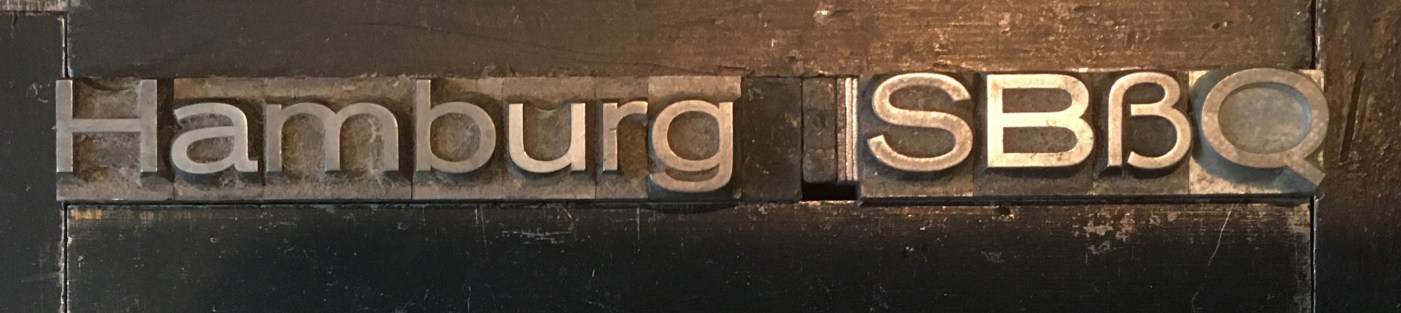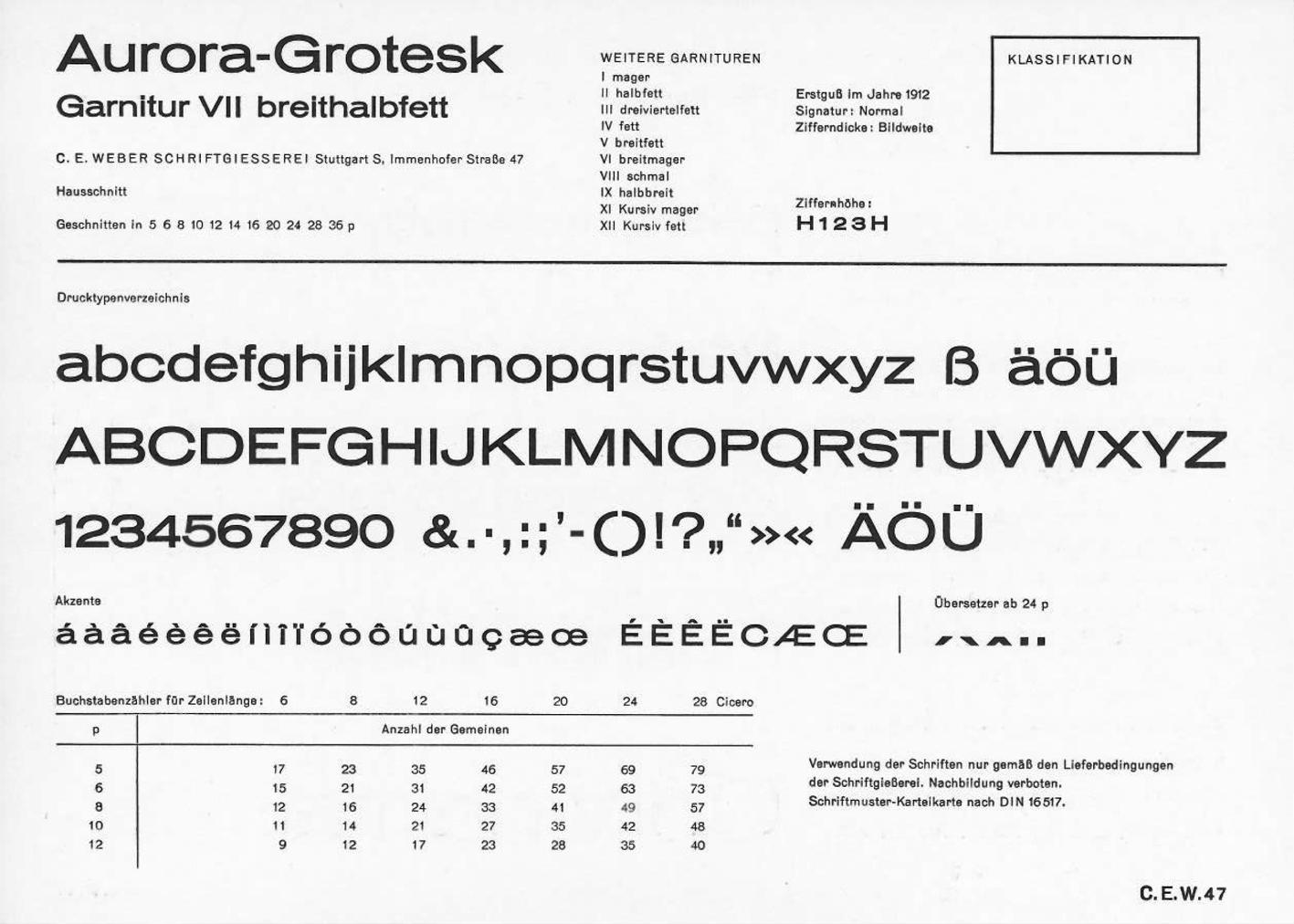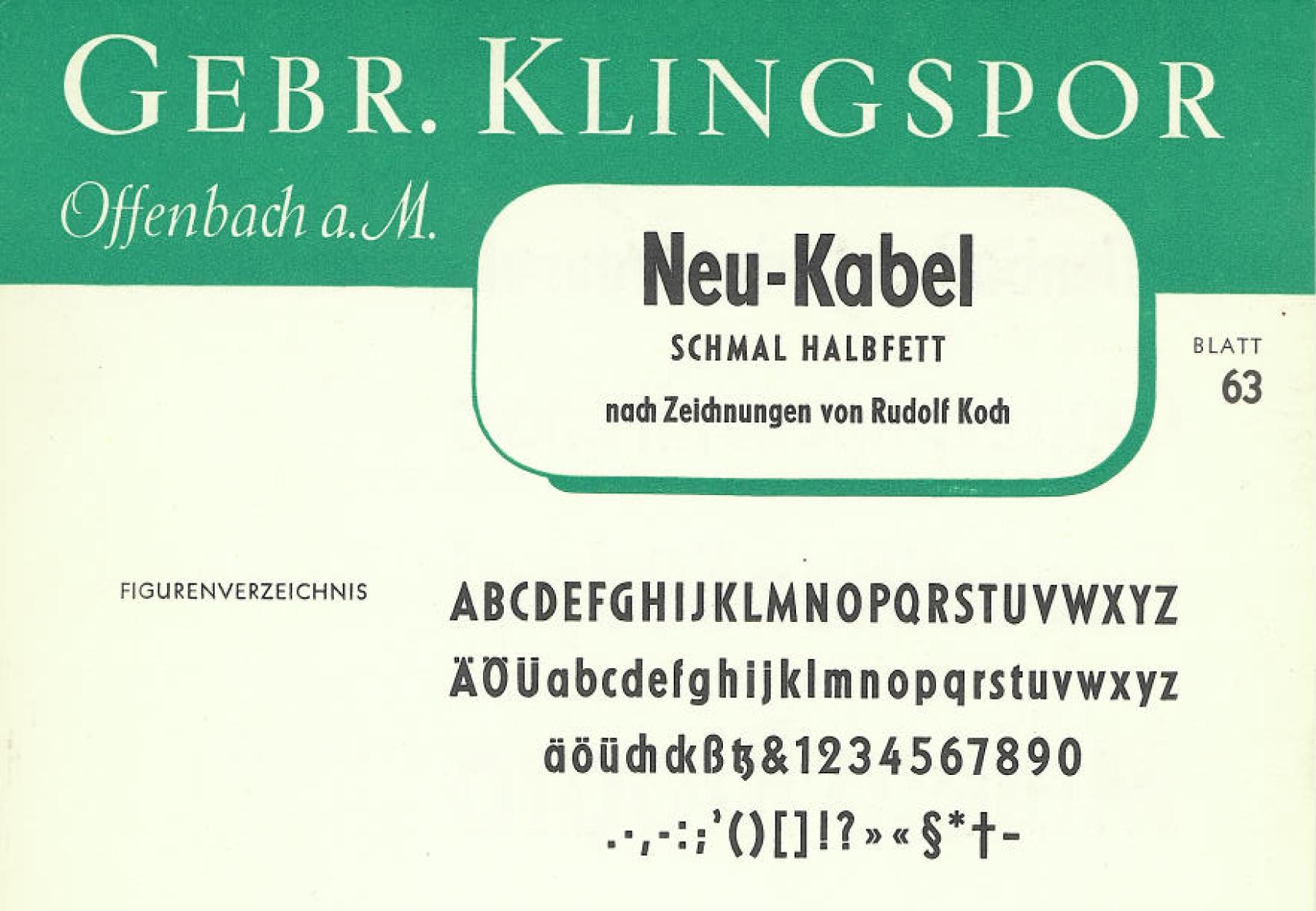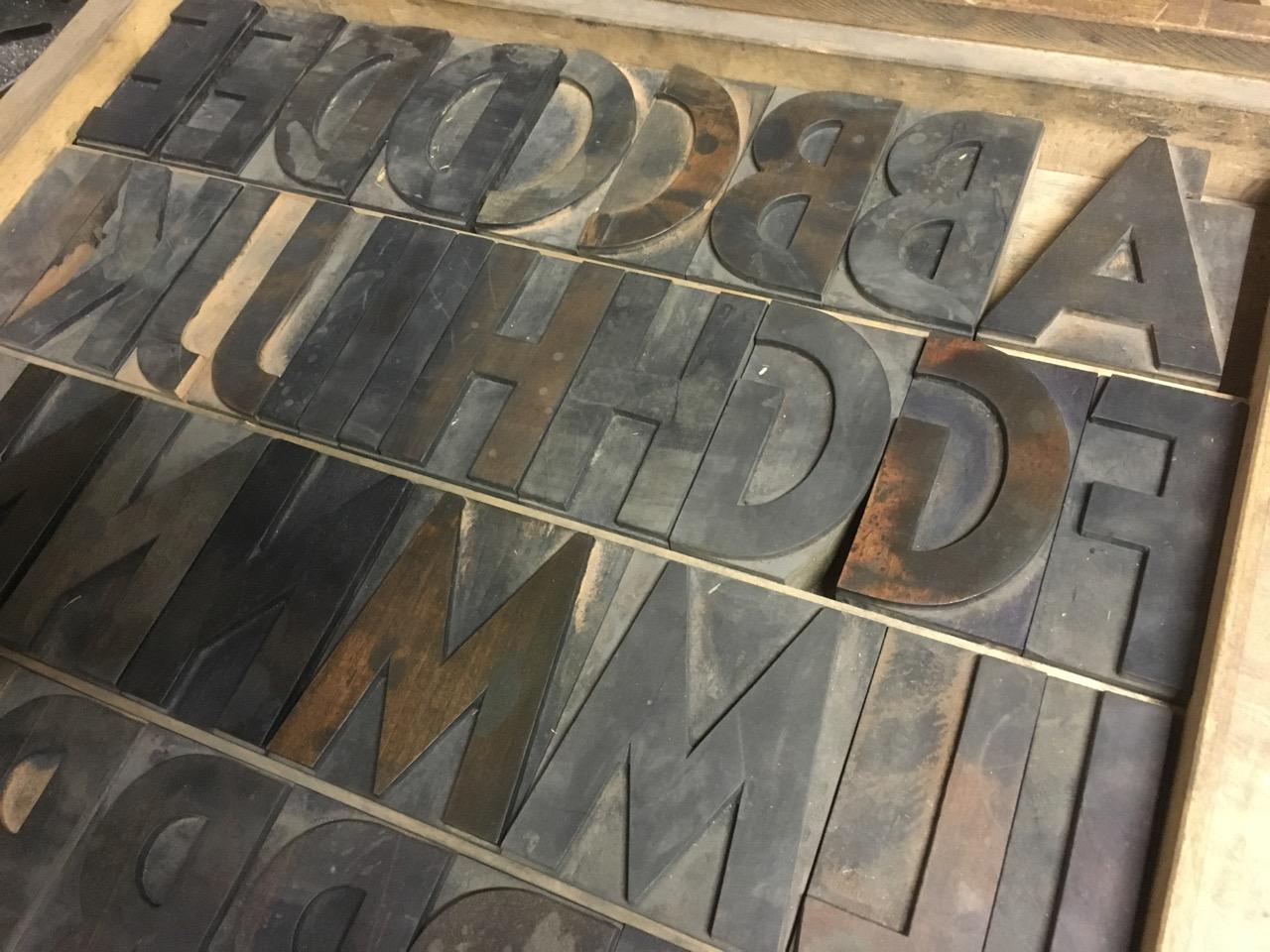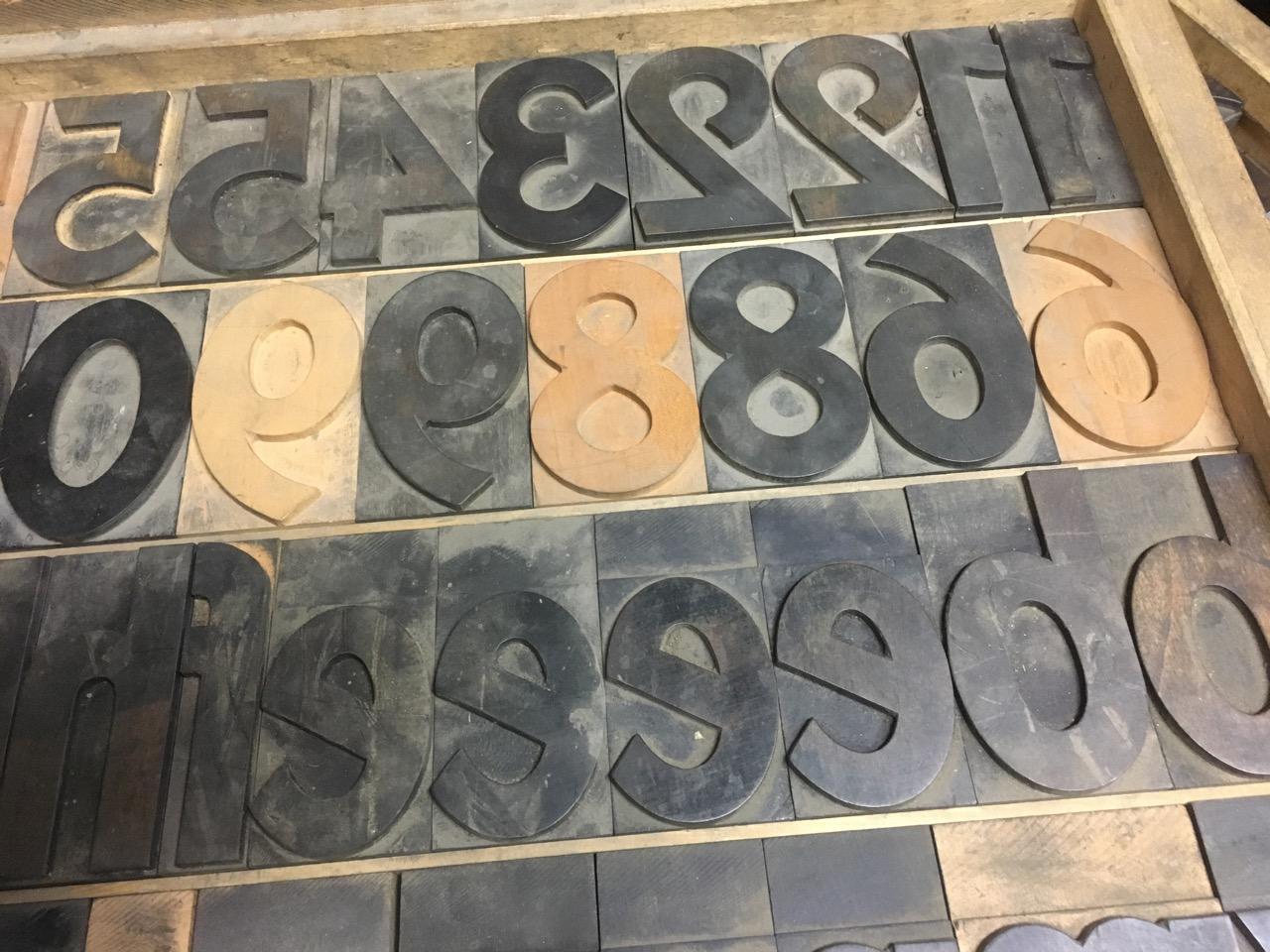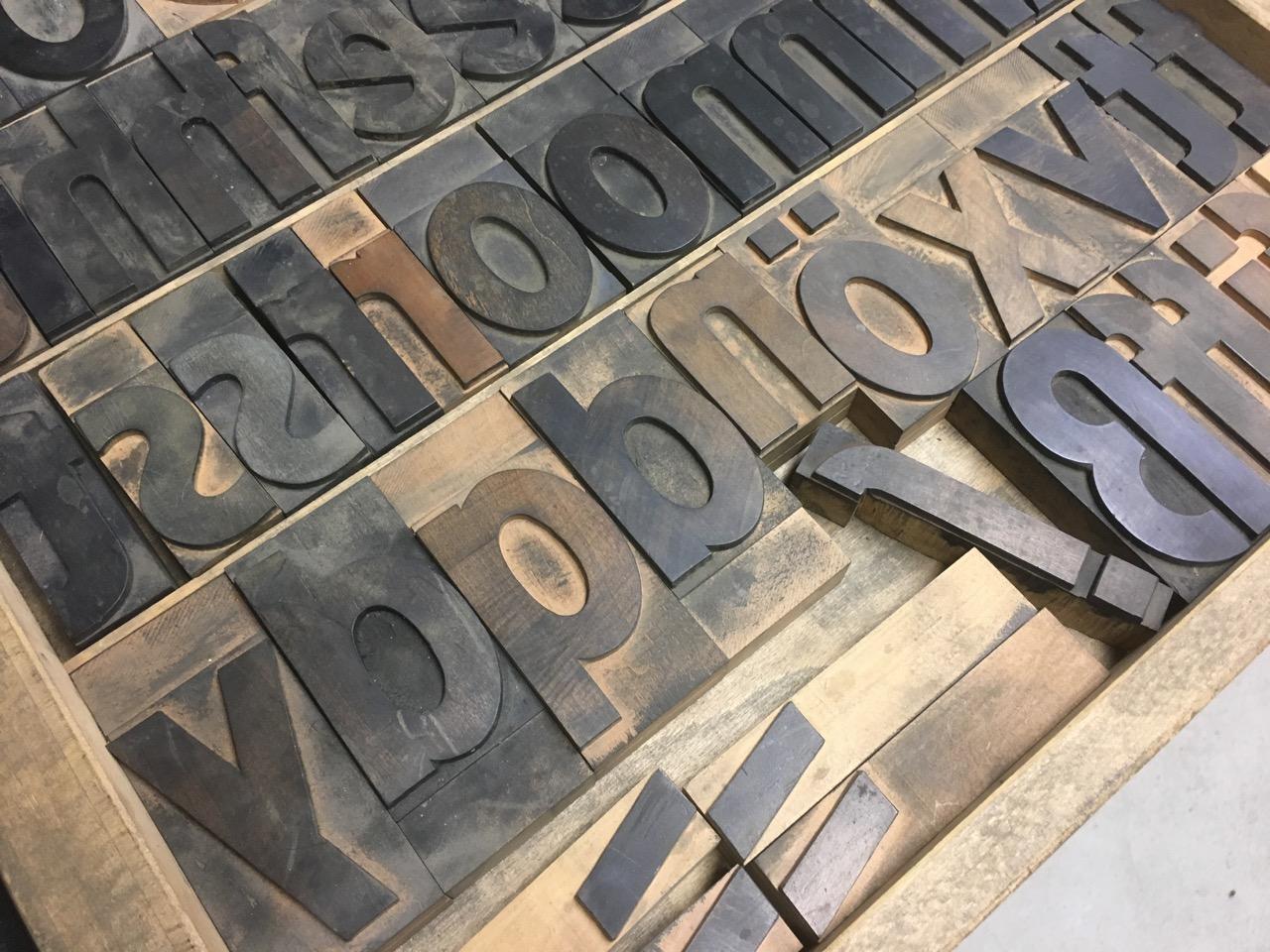
Identifikation Holzschriften
Unten ev. Akzidenz Skelett.
Korrigiere mich: es dürfte die hf.? breite Aurora Grotesk sein.
Tja, schwierig. Im Seemann finden sich schon lauter Klone mit identischem Bild. Akzidenz-Grotesk, Merkur, Viktoria-Grotesk, Elite-Grotesk, Klassische Grotesk, Edel-Grotesk, Aurora-Grotesk, Favorit-Grotesk … im Bezug auf das Wort Hamburg nicht zu unterscheiden.
... könnte die Kabel schmalhalbfett sein.
Vielleicht hat jemand ein komplettes gedrucktes Schriftmuster.
Sehe das auch so. Habe aber leider nur ein Muster der Bleisatz-Version, die doch ziemlich von der Holzschrift abweicht. Z. B. das "e". Trotzdem handelt es sich m. E. um die Schmal halbfette Kabel. Bei der gezeigten Holzschrift dürfte das "A" nicht dazupassen.
Vielen Dank! Ich hatte die Kabel wegen der starken Unterschiede zur normalbreiten Version erst ausgeschlossen, aber mit dem hier gezeigten Muster der schmalfetten ist es recht eindeutig. Na dann hoffe ich nun erstrecht, ich finde die fehlenden Buchstaben noch.